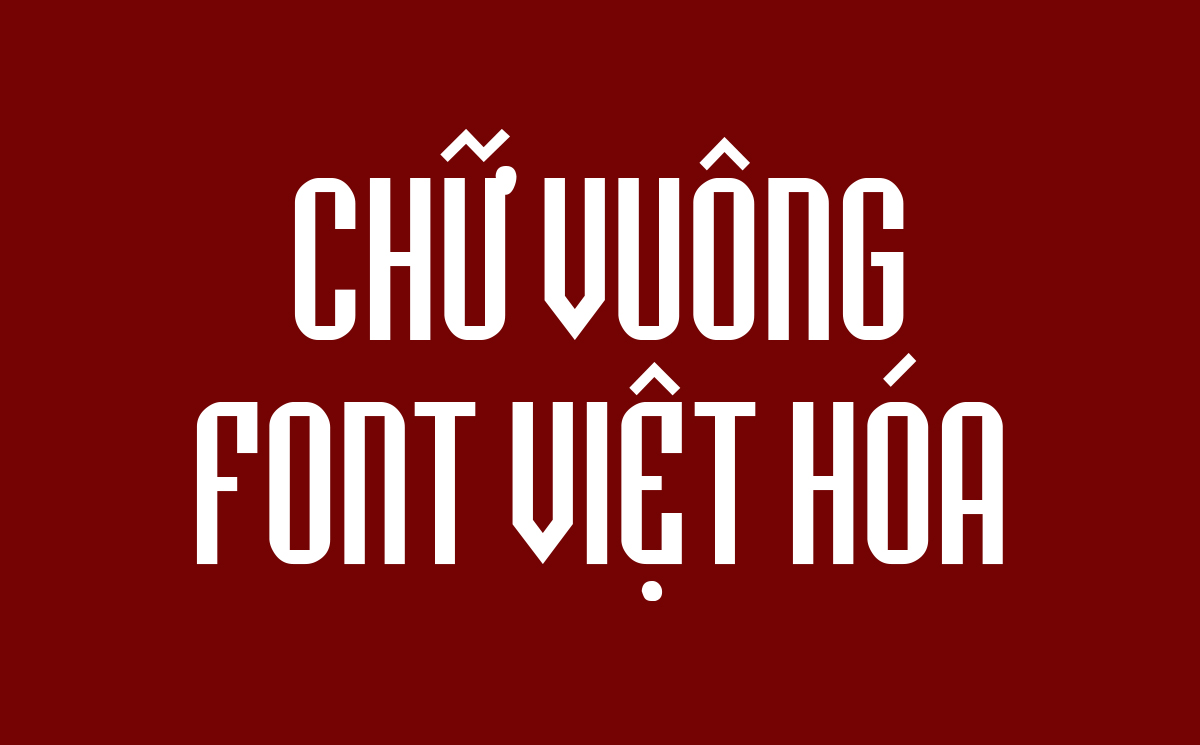
Font chữ vuông (hay còn gọi là Square font) là nhóm phông chữ được xây dựng dựa trên cấu trúc khung hình học vuông vức, tạo nên vẻ ngoài mạnh mẽ, hiện đại và vô cùng chắc chắn. Trong lĩnh vực đồ họa, nhóm font này thường được ưu tiên cho các thiết kế logo công nghệ, bao bì máy móc hoặc các ấn phẩm cần thể hiện sự bền vững. Doozypack.vn chia sẻ link download font chữ vuông đã được Việt hóa chỉn chu, giúp bạn dễ dàng ứng dụng vào sản xuất thực tế mà không lo lỗi hiển thị dấu tiếng Việt.
Tại sao nên sử dụng font chữ vuông trong thiết kế thương hiệu?
Khác với các dòng font script mềm mại, font chữ vuông tập trung vào tính đối xứng và sự cân bằng, mang lại những giá trị thị giác đặc trưng:
Tạo cảm giác ổn định, tin cậy và mạnh mẽ
Hình vuông vốn tượng trưng cho sự đất đai, nhà cửa và các cấu trúc bền vững. Khi ứng dụng vào font chữ, các góc cạnh vuông vức giúp thương hiệu truyền tải thông điệp về sự ổn định, uy tín và năng lực quản lý. Đây là lý do các tập đoàn tài chính, xây dựng hoặc sản xuất cơ khí thường chọn font chữ vuông làm phông nhận diện chủ đạo.
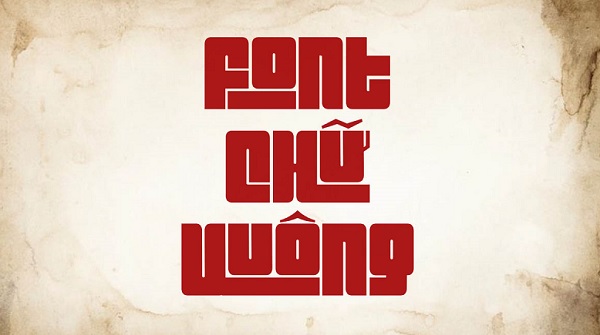
Tính ứng dụng cao cho các ngành công nghiệp và kỹ thuật
Cấu trúc chữ đơn giản, ít chi tiết thừa giúp font chữ vuông cực kỳ dễ đọc ngay cả ở khoảng cách xa hoặc trên các bề mặt gồ ghề. Trong thiết kế bao bì, font này giúp các thông số kỹ thuật, mã vạch hay tên sản phẩm trở nên rõ ràng và chuyên nghiệp hơn rất nhiều.
Top các bộ font chữ vuông Việt hóa phổ biến nhất hiện nay
Dưới đây là một số gợi ý font chữ vuông việt hóa được các designer tại Doozypack.vn tin dùng trong các dự án in ấn:
- Font Montserrat: Một trong những bộ font Sans-serif hình học kinh điển, mang vẻ đẹp hiện đại và tinh tế.
- Font Exo / Exo 2: Mang hơi hướng tương lai (futuristic), các nét vuông được bo góc nhẹ để tạo sự linh hoạt.
- Font Michroma: Một bộ font đậm chất công nghệ, vuông vức tuyệt đối, phù hợp cho các thiết kế tối giản và cơ khí.
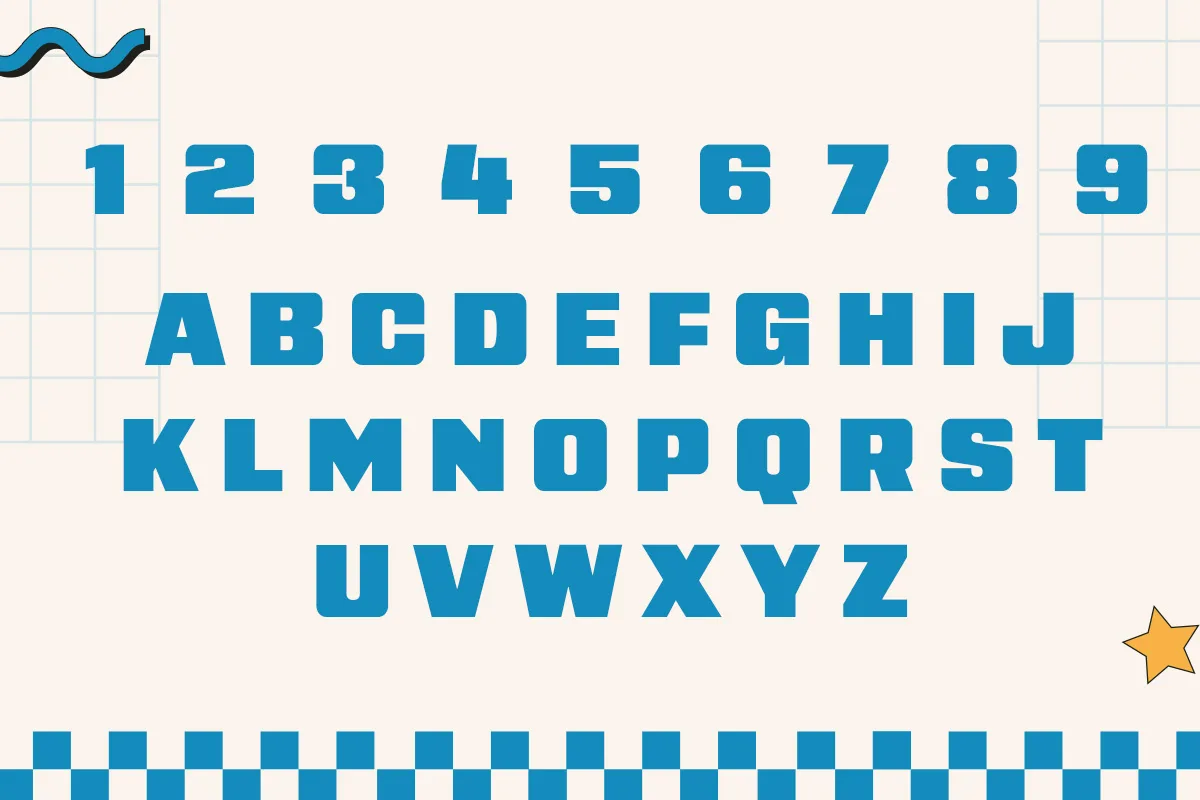
| Phong cách font | Đặc điểm nhận diện | Lĩnh vực ứng dụng |
| Square Sans | Vuông vức, không chân | Sản phẩm gia dụng, bao bì giấy cao cấp, túi giấy thời trang. |
| Techno / Futuristic | Cạnh sắc, góc nhọn | Linh kiện điện tử, phần mềm, gaming, bao bì đồ chơi công nghệ. |
| Blocky Style | Nét cực đậm, dày | Tiêu đề biển hiệu, poster sự kiện thể thao, thùng carton. |
Tư vấn từ chuyên gia: Nếu bạn thiết kế bao bì cho sản phẩm điện tử, hãy chọn nhóm Techno Square để tăng tính hiện đại. Ngược lại, nếu thiết kế túi giấy cho các shop thời trang nam, nhóm Square Sans sẽ tạo cảm giác thanh lịch và nam tính hơn.
Ứng dụng font chữ vuông trong ngành sản xuất bao bì giấy
Tại Doozypack.vn, chúng tôi thường xuyên xử lý các mẫu thiết kế sử dụng font chữ vuông và nhận thấy hiệu quả ấn tượng trên thành phẩm:
- Hộp đựng linh kiện điện tử: Các thông số như số seri, công suất được trình bày bằng font chữ vuông giúp người dùng dễ dàng tra cứu thông tin.
- Túi giấy thời trang nam: Font chữ vuông khổ lớn in chính giữa túi giấy tạo nên một diện mạo mạnh mẽ, thu hút sự chú ý của khách hàng ngay từ cái nhìn đầu tiên.
- Tem nhãn sản phẩm: Font chữ vuông có độ tương phản cao, giúp tem nhãn nổi bật ngay cả khi dán trên các bề mặt hộp tối màu.
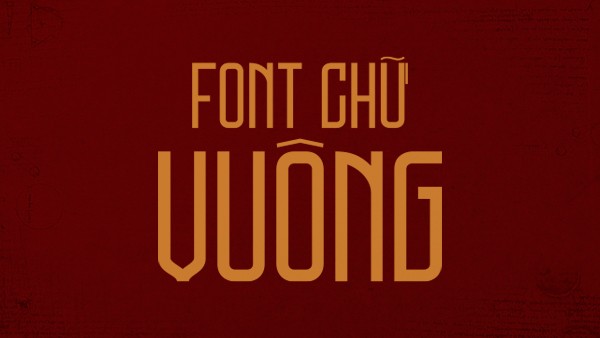
Khi đưa thiết kế sử dụng font chữ vuông vào sản xuất thực tế, bạn cần lưu ý một số yếu tố kỹ thuật để tránh hỏng bản in:
- Hiện tượng tràn mực (Ink gain): Với các bộ font chữ vuông có nét cực đậm (Black style), khoảng trắng bên trong chữ (như lỗ chữ A, O, D) thường rất nhỏ. Khi in trên giấy có độ thấm mực cao, mực có thể tràn làm lấp mất các khoảng trắng này. Bạn nên chọn style font vừa phải hoặc tăng khoảng cách chữ (Tracking).
- In chữ âm bản (Negative Print): Khi in font chữ vuông màu trắng trên nền tối, chữ có xu hướng trông mảnh đi. Bạn cần bù trừ bằng cách tăng độ dày của font trong file thiết kế.